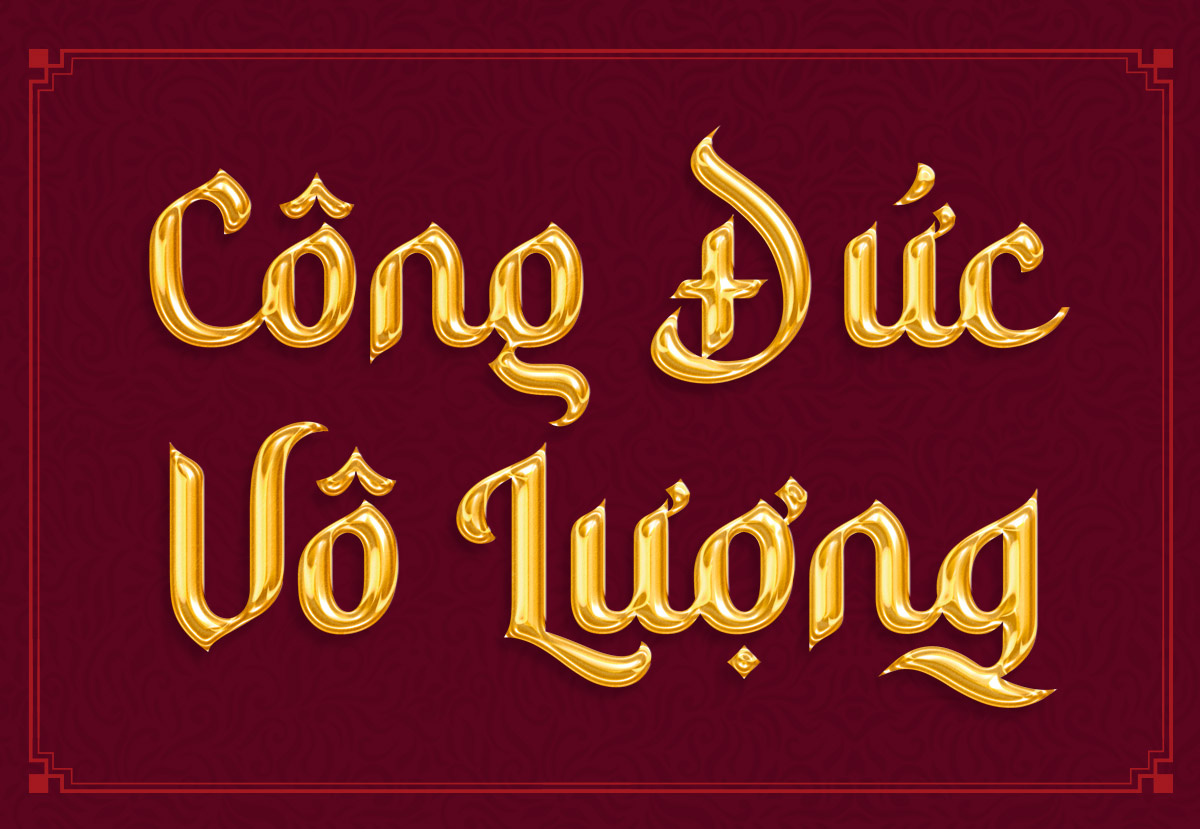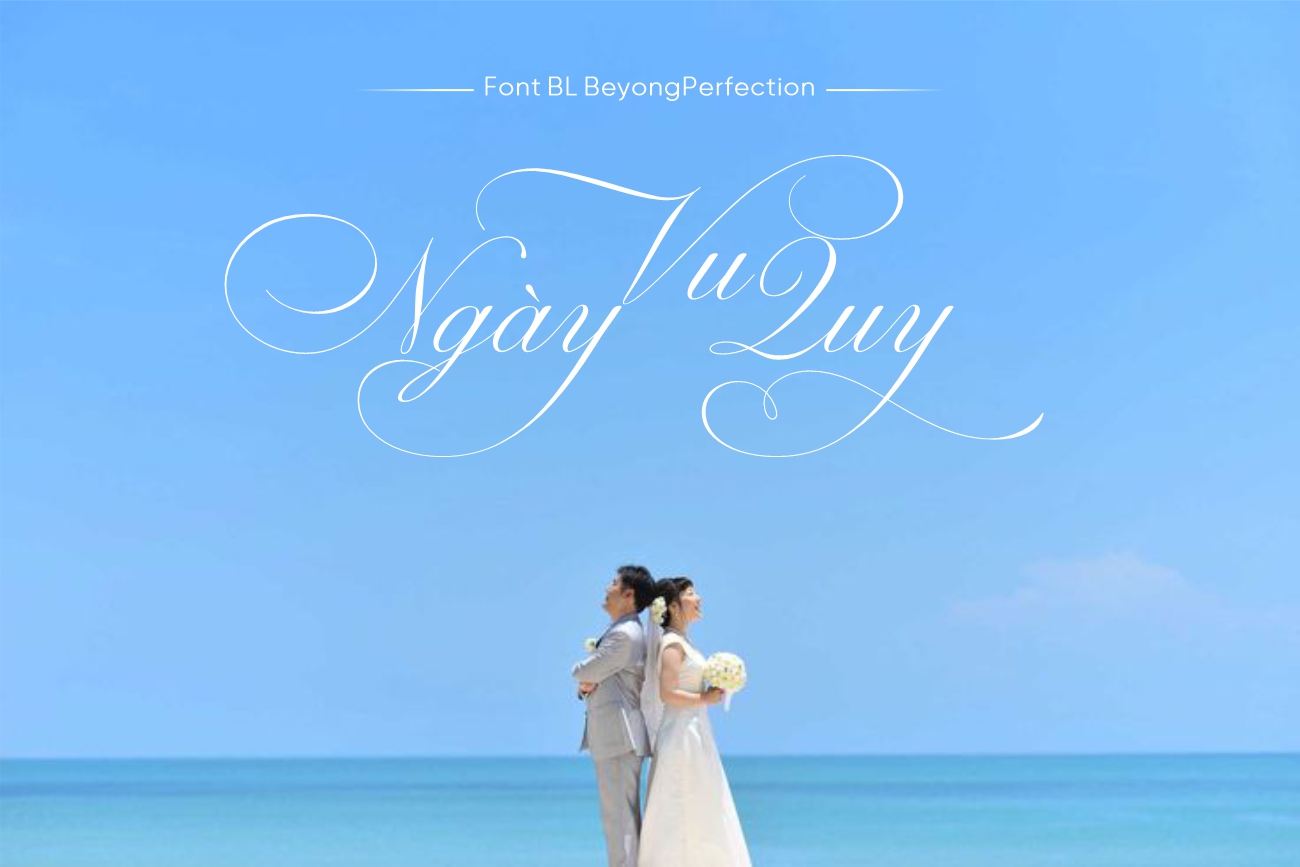
Tổng Hợp 13 Font Chữ Cổ Việt Hóa Cho Thiết Kế Lịch Sử
Bộ sưu tập 13 font chữ cổ Việt hóa đẹp nhất 2025, mang phong cách thư pháp, cổ điển và hoài niệm. Lý tưởng cho thiết kế văn hóa, thương hiệu di sản.
Tổng Hợp 13 Font Chữ Cổ Việt Hóa Cho Thiết Kế Lịch Sử
Bạn đang tìm kiếm font chữ cổ Việt hóa độc đáo? Tải ngay bộ font chữ cổ Việt hóa tuyệt đẹp – từ font thư pháp trang trọng đến nét chữ hoài cổ mộc mạc. Bộ sưu tập hoàn hảo giúp bạn tạo nên những tác phẩm thiết kế giàu giá trị văn hóa, tinh tế và đầy cảm xúc.
Font chữ cổ không chỉ là kiểu chữ, mà còn là hồi ức lịch sử và nét đẹp truyền thống. Bộ sưu tập font chữ cổ Việt hóa này sẽ mang sự trang trọng, hoài niệm vào mọi dự án thiết kế đòi hỏi chiều sâu, như ấn phẩm văn hóa và branding cao cấp.
Trong bài viết này, Fontdep.vn sẽ giới thiệu và phân tích chuyên sâu về thế giới font chữ cổ, cùng danh sách 13 font chữ cổ Việt hóa đẹp nhất, giúp bạn tìm thấy kiểu chữ hoàn hảo để đưa vẻ đẹp lịch sử vào thiết kế của mình.
Font Chữ Cổ: Giá Trị Nghệ Thuật Và Ứng Dụng Trong Thiết Kế Hiện Đại
Font Chữ Cổ là Gì?
Font chữ cổ (Historical/Vintage Fonts) là các kiểu chữ được thiết kế dựa trên hoặc mô phỏng lại các phong cách chữ viết, in ấn, hoặc thư pháp từ những giai đoạn lịch sử và văn hóa cụ thể. Chúng được chia thành ba nhóm chính, thể hiện qua các đặc điểm sau:
Đặc điểm nổi bật của 3 nhóm chính:
• Font Cổ Điển (Classic/Serif): Nét chữ có chân (Serif) dày dặn hoặc thanh mảnh, độ tương phản cao, mang tính trang trọng và quyền lực. Thời kỳ La Mã, Phục Hưng, Baroque (thường thấy trong sách in, tiêu đề báo chí).
• Font Hoài Cổ (Vintage/Retro): Nét chữ bo tròn, thường là Sans Serif hoặc Slab Serif, gợi cảm giác thân thiện, ấm áp và hoài niệm. Thập niên 1920-1980 (phong cách Art Deco, Mid-Century Modern, Bao Cấp Việt Nam).
• Font Cổ Trang/Thư Pháp: Nét chữ bay bổng, uốn lượn, mô phỏng bút lông, thư pháp, hoặc chữ triện. Văn hóa Á Đông (Trung Quốc, Việt Nam, Nhật Bản) thời phong kiến.
Ứng Dụng Nổi Bật Của Font Chữ Cổ Trong Thiết Kế
Font chữ cổ có tính ứng dụng rất đa dạng, đặc biệt quan trọng trong các ấn phẩm cần truyền tải chiều sâu lịch sử và sự trang trọng:
• Ấn phẩm Văn hóa/Lịch sử: Sử dụng font Serif Lịch sử (ví dụ: TH LichSu 1) cho tiêu đề sách, tạp chí chuyên ngành, tài liệu bảo tàng, hoặc các dự án nghiên cứu cần sự nghiêm cẩn.
• Branding Cao cấp/Di sản: Áp dụng font Script/Serif Trang trí (ví dụ: Zahra, SVN Nubya) cho logo thương hiệu rượu, trà, thời trang thủ công, hoặc các sản phẩm có giá trị di sản.
• Thiết kế Hoài cổ/Retro: Dùng font Hoài cổ (ví dụ: TH HoaiCo, TH HC Calvous) cho poster, bao bì sản phẩm tái hiện thập niên 70-90, hoặc trang trí quán cà phê/phim ảnh phong cách Vintage Việt Nam.
• Ấn phẩm Tôn giáo/Thư pháp: Sử dụng font Thư pháp (ví dụ: Thư Pháp Đại Tự) cho câu đối, lịch Tết, thiệp mời sự kiện tôn giáo, hoặc các ấn phẩm mang tính tâm linh, cần sự tĩnh lặng.
Danh Sách 13 Font Chữ Cổ Việt Hóa Tuyệt Đẹp Cho Mọi Dự Án
Fontdep.vn đã tuyển chọn 15 font chữ cổ tiêu biểu, được Việt hóa hoàn chỉnh, bao gồm đủ các phong cách từ cổ trang, thư pháp, đến hoài cổ retro.
1. Font Script Cổ trang Zahra Việt Hóa – Bay bổng, Tinh tế
Font Zahra Việt Hóa là kiểu chữ Script với nét bay bổng, uốn lượn tinh tế, mang đậm phong cách cổ trang và hơi hướng chữ Ả Rập. Thường dùng làm tiêu đề chính, logo cho các thương hiệu trà, rượu, hoặc dịch vụ làm đẹp cao cấp.
2. Font Serif Trang trí SVN Nubya Việt Hóa – Cổ trang, Văn Hóa
Font SVN Nubya là một font chữ sans-serif độc đáo, Điểm đặc biệt của font nằm ở cách pha trộn giữa các nét tối giản hiện đại và cảm hứng từ thư pháp truyền thống, tạo nên một cảm giác trang trọng, tinh tế nhưng vẫn dễ đọc và dễ ứng dụng.
3. Font Thư pháp LNTN Daybreaker Việt Hóa – Lễ hội, Họa tiết
LNTN Daybreaker Việt Hóa là font thư pháp độc đáo, kết hợp giữa nét chữ viết tay mạnh mẽ và các họa tiết trang trí (hoa lá, mây) cho cảm giác lễ hội, thường dùng cho ấn phẩm Trung thu, Tết Nguyên Đán, hoặc bao bì truyền thống.
4. Font Serif Lịch sử TH LichSu 1 – Nghiêm cẩn, Cổ điển
TH LichSu 1 là font Serif cổ điển với độ tương phản vừa phải, rất nghiêm cẩn, phù hợp cho các ấn phẩm về lịch sử Việt Nam, tài liệu nghiên cứu, hoặc bảng chỉ dẫn bảo tàng.
• Tác giả gốc: Đang update
• Việt hóa bởi: Font TH
• Tải về: TH LichSu 1
5. Font Thư pháp Tôn giáo TH Hidayatullah Việt Hóa – Tĩnh lặng
TH Hidayatullah Việt Hóa mô phỏng nét thư pháp Hồi giáo (Ả Rập), mang lại cảm giác thiền định, tĩnh lặng. Thích hợp cho các ấn phẩm Phật giáo, Nhà Chùa, hoặc các thiết kế liên quan đến tôn giáo và tâm linh.
6. Font Cổ điển Á Đông TH China 1 Việt Hóa – Tinh xảo
TH China 1 Việt Hóa mang đậm phong cách cổ điển Trung Quốc, với nét chữ tinh xảo, thường thấy trong các ấn phẩm dã sử hoặc menu nhà hàng Á Đông sang trọng.
7. Font Thư pháp Đại tự – Mạnh mẽ, Dứt khoát
Font Thư Pháp Đại Tự có nét chữ mạnh mẽ, dứt khoát, mô phỏng thư pháp Việt Nam. Thường dùng cho câu đối, ấn phẩm Lịch Tết hoặc các tiêu đề cần sự trang trọng và uy lực.
• Tác giả gốc: Đức Thủy
Font Chữ Thư Pháp Đại Tự Tiếng Việt - Thiết Kế Bởi Font Zin
8. Font Cổ trang Nhật Bản TH Nhat Ban 1 Việt Hóa – Zen, Tối giản
TH Nhat Ban 1 Việt Hóa mang phong cách chữ viết Nhật Bản, gợi cảm giác Zen (thiền định), tối giản và tinh tế. Phù hợp cho thiết kế trà đạo, võ thuật hoặc du lịch Nhật Bản.
ii
9. Font Gothic TH LichSu 3 Việt Hóa – Văn hóa, Nghiêm túc
TH LichSu 3 Việt Hóa là font chữ mang hơi hướng Gothic/Cổ điển châu Âu, nhưng đã được Việt hóa để sử dụng trong các ấn phẩm về văn hóa, lịch sử nghiêm túc hoặc bìa sách triết học cổ.
ii
10. Font Retro Bao Cấp TH HC Calvous – Mộc mạc, Đơn giản
TH HC Calvous là font chữ mang phong cách hoài cổ 'thời bao cấp', với nét chữ mộc mạc, đơn giản, gợi cảm giác chân thật về quá khứ Việt Nam thời kỳ 1970-1990.
• Tác giả gốc: Hendry Juanda
• Việt hóa bởi: Font TH
• Tải về: TH HC Calvous
Font chữ tiếng Việt phong cách hoài cổ của thời bao cấp TH - HC Calvous
11. Font Hoài Cổ Viết tay TH HoaiCo 3 Việt Hóa – Gần gũi
TH HoaiCo 3 Việt Hóa mô phỏng nét viết tay cũ, tạo cảm giác hoài niệm và gần gũi như chữ viết trong sổ tay thời xưa. Đây là lựa chọn lý tưởng cho thiết kế bìa sách, áp phích phim hoặc các ấn phẩm muốn tái hiện lại không khí mộc mạc của Việt Nam những năm 80.
[Tải Xuống] Phông Chữ Xưa Thời Bao Cấp Việt Hóa Đẹp – TH Hoaico 3
12. Font Retro Mềm mại TH HoaiCo 2 Việt Hóa – Thân thiện
TH HoaiCo 2 Việt Hóa là font hoài cổ nhưng có nét mềm mại, thân thiện hơn so với TH HoaiCo 3. Thường dùng cho thiết kế ẩm thực truyền thống hoặc bao bì bánh kẹo xưa.
TH Hoaico 2 – Font Chữ Việt Hóa Mang Hơi Thở Thời Bao Cấp, Mộc Mạc và Hoài Niệm
13. Font Serif Cao cấp TH Hustle Culture – Sang trọng
TH Hustle Culture là font Serif cổ điển Châu Âu, được thiết kế với độ tương phản cao, mang lại cảm giác sang trọng, trang nhã. Lý tưởng cho tiêu đề tạp chí, logo thương hiệu thời trang cao cấp.
• Tác giả gốc: Letterhend Studio
• Việt hóa bởi: Font TH
• Tải về: TH Hustle Culture
Hướng Dẫn Cài Đặt Font Việt Hóa Nhanh Chóng
Trên Windows:
1. Tải file font (.ttf hoặc .otf).
2. Nhấp chuột phải → chọn Install/Cài đặt.
3. Mở Photoshop, Illustrator hoặc Canva để sử dụng ngay.
Trên macOS:
1. Mở ứng dụng Font Book.
2. Kéo thả file font vào cửa sổ.
3. Nhấn Install Font và kiểm tra các ký tự có dấu (ư, ă, ê, đ…) để đảm bảo hiển thị đúng.
Kết Luận
Bộ sưu tập font chữ cổ Việt hóa này là một công cụ thiết yếu cho bất kỳ nhà thiết kế nào mong muốn truyền tải chiều sâu lịch sử, sự trang trọng, và nét hoài niệm vào tác phẩm của mình.
Fontdep.vn đã tuyển chọn và Việt hóa cẩn thận 13 font chữ cổ tiêu biểu, bao gồm các phong cách từ thư pháp Á Đông, cổ điển Châu Âu, đến retro Việt Nam. Bộ font này đảm bảo:
• Việt hóa Hoàn hảo: Hỗ trợ đầy đủ các ký tự có dấu trong tiếng Việt, loại bỏ lỗi font, giúp nội dung hiển thị trọn vẹn và chuyên nghiệp.
• Giá trị Văn hóa: Cung cấp giải pháp chuyên biệt cho các dự án đòi hỏi sự am hiểu sâu sắc về văn hóa và lịch sử.
• Tính Ứng dụng Cao: Font có thể được phối hợp linh hoạt với các kiểu chữ hiện đại để tạo ra sự tương phản hài hòa, nâng cao đẳng cấp cho thương hiệu.